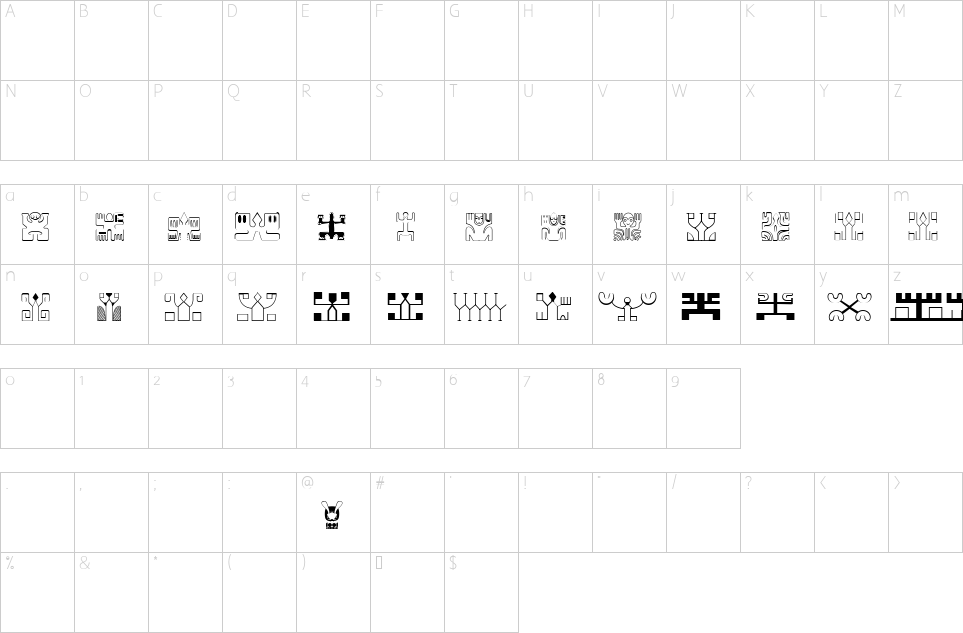
Descubra a beleza de Polynesien Etua Font, uma fonte que combina elegância e naturalidade em cada caractere. Desenvolvida pelo designer desconhecido, esta fonte oferece uma paleta de letras que vai desde linhas finas até texturas mais ricas, proporcionando diversidade para diferentes ambientes de design. Seja você um designer gráfico ou um escritor, Polynesien Etua Font é uma escolha ideal para quem busca tanto qualidade quanto uma sensação de liberdade criativa. Baixe já, é gratuito e disponível tanto para o sistema operacional Windows quanto para o Mac. Descubra por si mesmo os benefícios de adicionar esta fonte única à sua biblioteca de recursos gráficos.